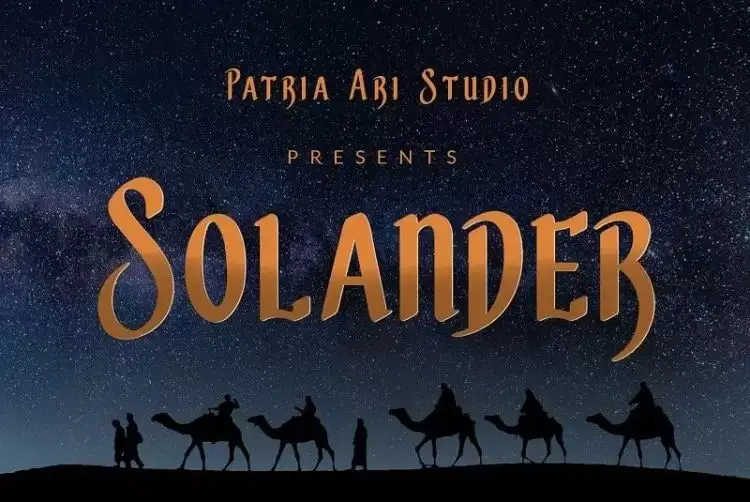
Solander Display Font
A Solander Display Font é uma opção perfeita para quem busca a simplicidade de um tipo moderno, mas com um sabor vintage. Criada pelo Patria Ari Typestudio na categoria de fontes display, esta elegante fonte se destaca por sua minimalista e atual aparência, ideal para diversos projetos gráficos. Seja para criar logotipos e identidades de marca, headlines, materiais publicitários ou até mesmo em etiquetas e água-marinhas para eventos especiais, a Solander proporciona um toque único ao seu design. Com uma versatilidade impressionante, esta fonte é perfeita para estilos variados. Permite criar identificações de marca modernas e inovadoras, ou dar um ar retrô aos elementos gráficos mais tradicionais. Seja em materiais impressos, como cartazes, embalagens ou até mesmo na fotografia onde desejar adicionar uma pegada vintage sem sacrificar a simplicidade e a estética contemporânea. Ideal tanto para personalizar seu trabalho quanto para quem busca um toque especial nos projetos de logotipos e identidades visuais, a Solander é uma fonte display que combina criatividade com simplicidade. Seja você um profissional da design ou apenas alguém que aprecia uma boa fonte para seus trabalhos, esta Solander Display Font pode transformar seu projeto em algo único e memorável.